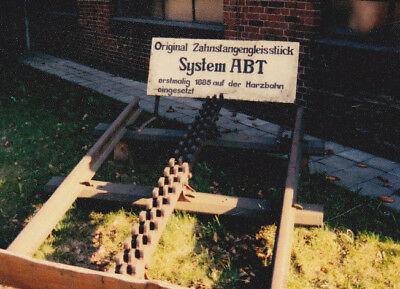
Schrift Harzer Zahnradbahn
Dieses Schild soll in einem 3d Projekt besser zu sehen sein und nachgebaut werden. hier geht es allein um die Schrift.
Sieht mir sehr nach gemalt aus...
Für die erste Zeile  würde ich eine Souvenir Condensed empfehlen, die zweite Zeile sieht wegen des A und des T sehr nach Jugendstil aus und "erstmalig..." sieht nach Futura aus.
Allerdings würde ich das gesamte Schild in einer einzigen Schrift nachsetzen - also Futura - und nur "System ABT" in einer Jugendstiligen.
Vielleicht haben die Schriftenkenner hier noch andere Ideen...
Nun ja das Bild ist historisch und es soll in eine 3d-Umgebung eingefügt werden. wahrscheinlich  muss alles so bleiben wie es ist um es wieder zuerkennen. Die Besagten Schriften werde ich mal testen sofern sie kostenlos sind, da ja das was ich mache kostenfrei bleiben sollte.
Gemalt sieht mir das auch aus, allerdings von einem Eisenbahner der keine Typo-Kenntnisse hatte. Das sah man auch oft auf Schildern der Deutschen Reichsbahn ins soz. Ausland wie es damals so "schön" hieß.
Hier mal so gemischte Beispiele: Einige Schilder kamen gelegentlich auch von der DB die allerdings sehr schnell vom Personal der DR sozialistisch umgelagert und verteilt wurden oder privat gesammelt.
Aha :-? Wie kommst du darauf, dass es ein Eisenbahner* war und, dass er keine „typografischen Kenntnisse“ hatte? Es ist jetzt kein Kunstwerk, soll es auch nicht sein, aber wirklich verunglückt ist das auch nicht. Das Schild hat anscheinend auch nix mit regulärem Bahnbetrieb zu tun, es dient ja wohl als Ausstellungsbeschilderung.
Dann musst du es wohl nachmalen …
Insider Kentnisse, ja es soll typografisch nur nachgebaut werden weil die fotos zu schlecht sind.